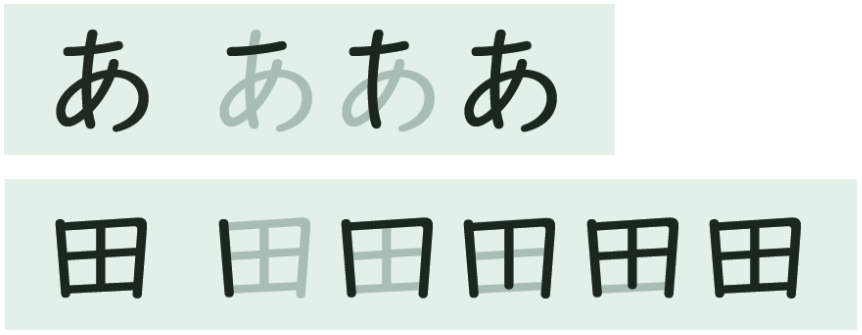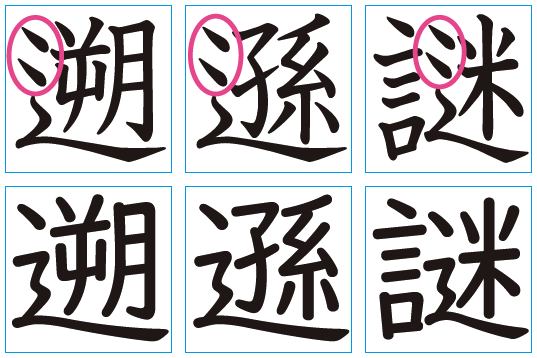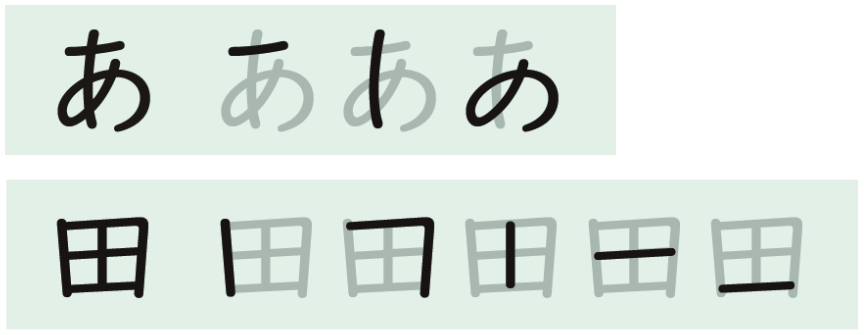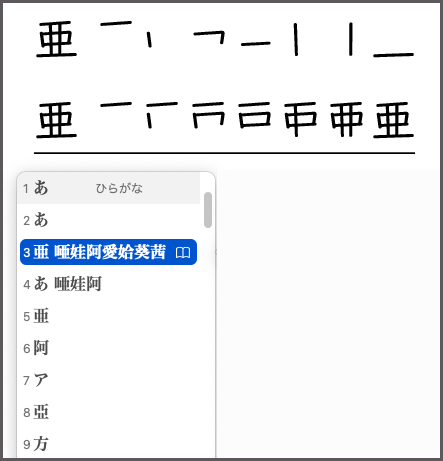
【筆順フォントとは】
UDデジタル教科書体 筆順フォントとは、学習指導要領に沿った字形「UDデジタル教科書体」を、書き順に沿ったストロークごとに一文字として、文字を書いていく過程を収録しているフォントです。
UDデジタル教科書体 筆順フォントには、TypeAとTypeBがございます。
TypeA
書き順に沿って、一画ずつバラバラに表示できます。
※アプリケーションによる加工使用例(グレー表示部分は、グリフを重ねています)
TypeB
書き順に沿って、一画ずつ増やして表示できます。
※アプリケーションによる加工使用例(グレー表示部分は、グリフを重ねています)
【『遡』『遜』『謎』の3文字について】
『遡』『遜』『謎』の3文字は、2010年改訂常用漢字表の明朝体では「2点しんにょう」で表示されていますが、UDデジタル教科書体 筆順の字形は「1点しんにょう」で統一されています。
ただし、「UDデジタル教科書体 筆順フォント」には、この3文字の「2点しんにょう」も特別に収録しています。
UDデジタル教科書体 筆順フォントは、数字とかな・漢字の筆順を示す書体です。